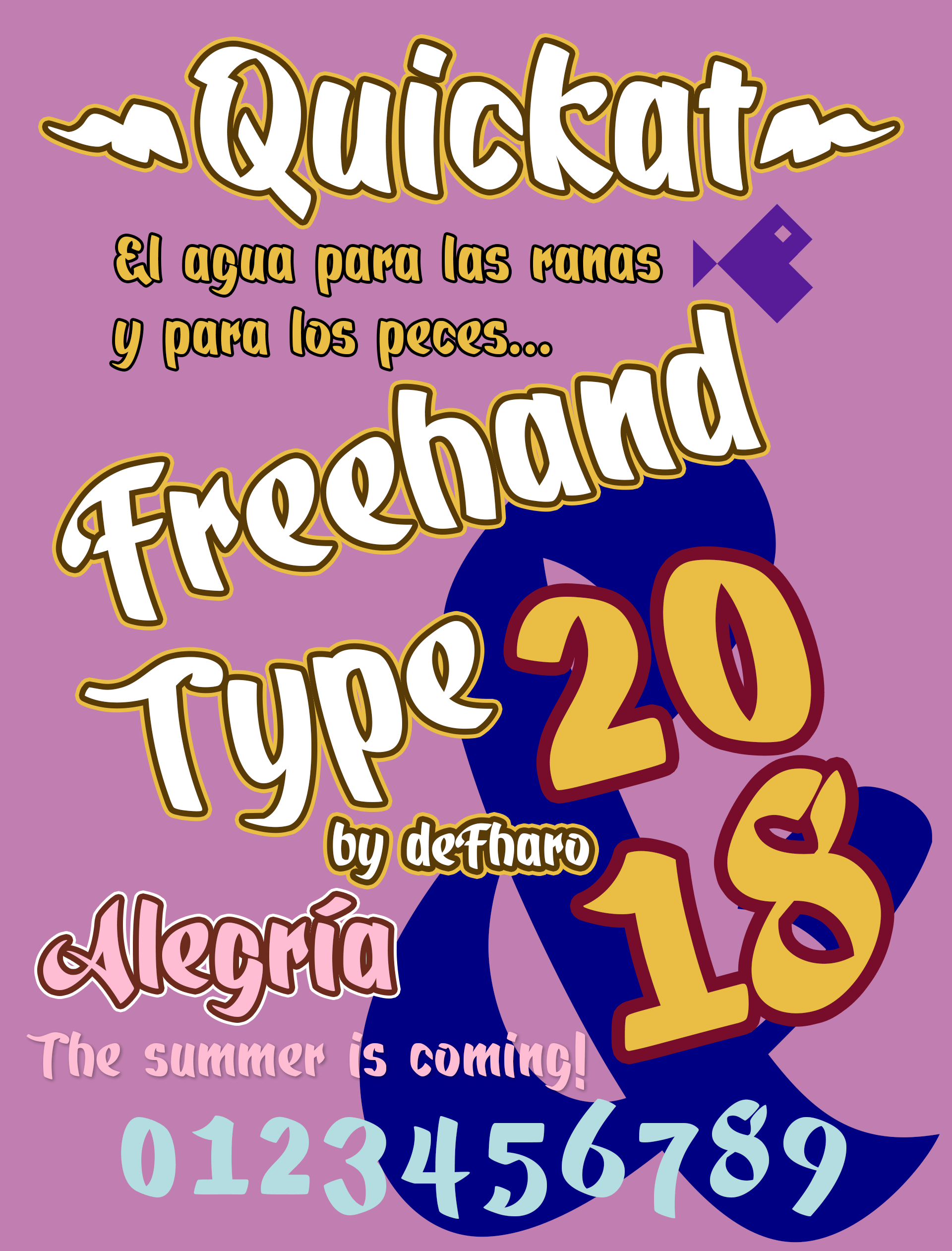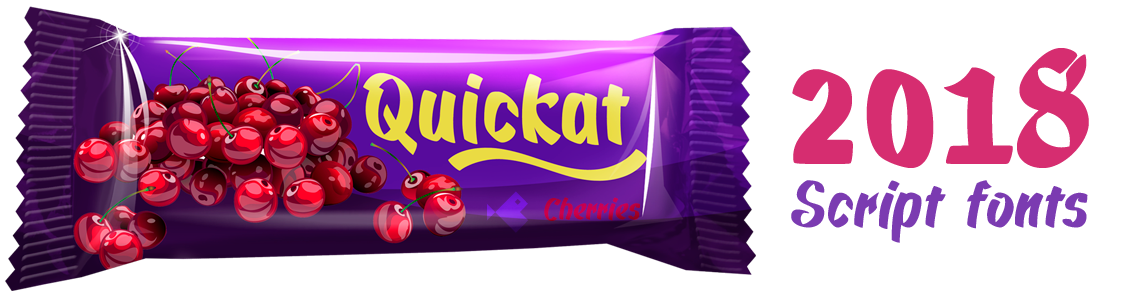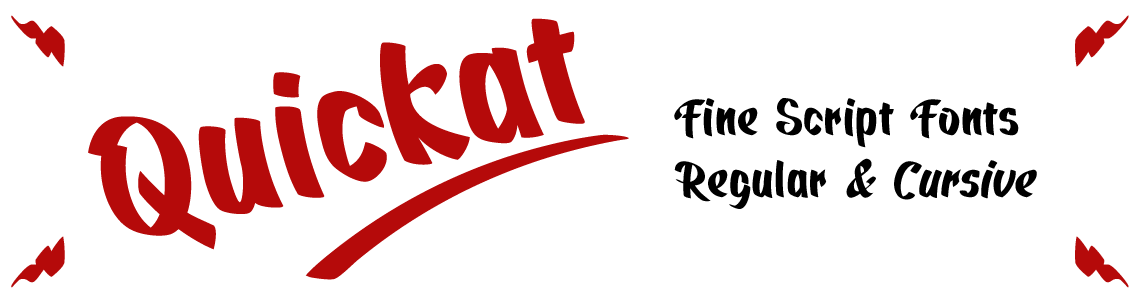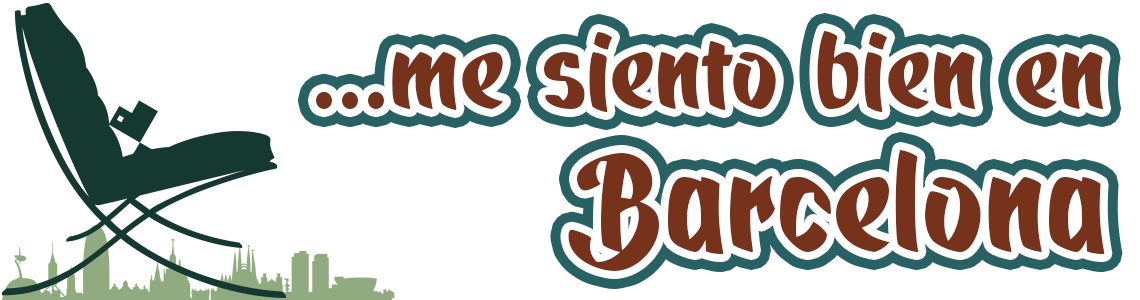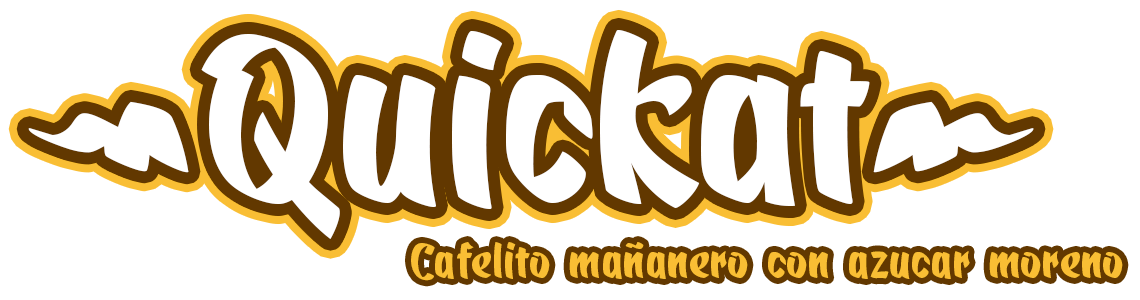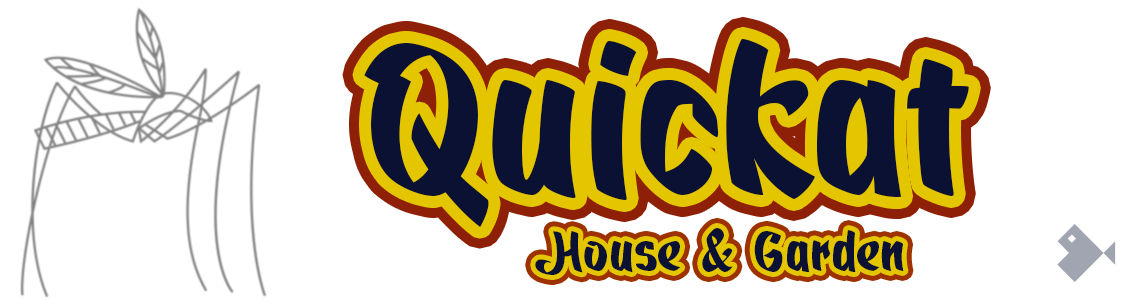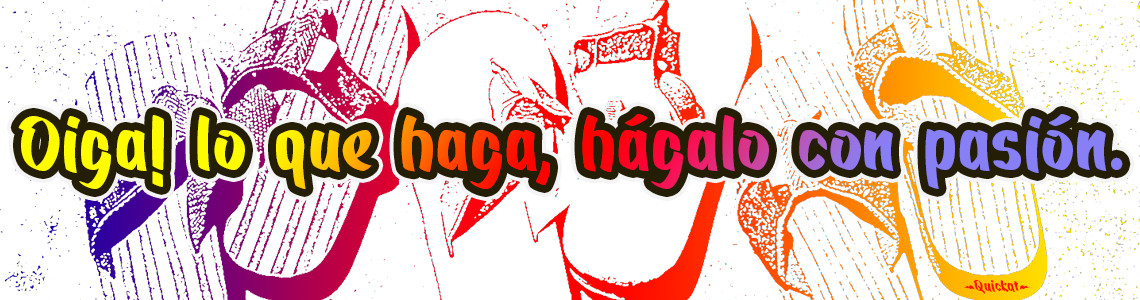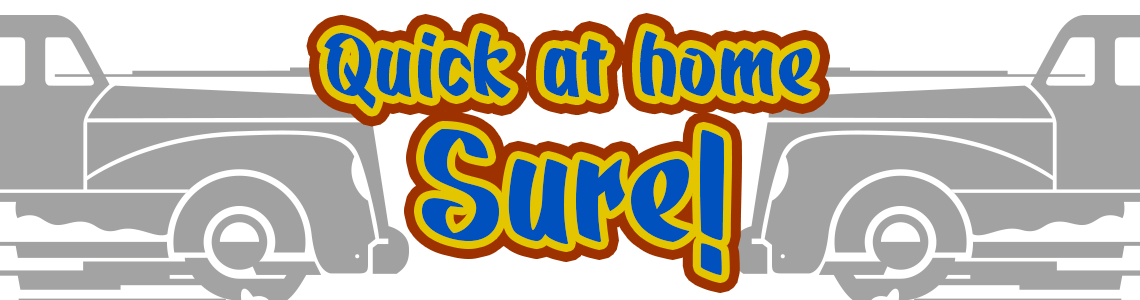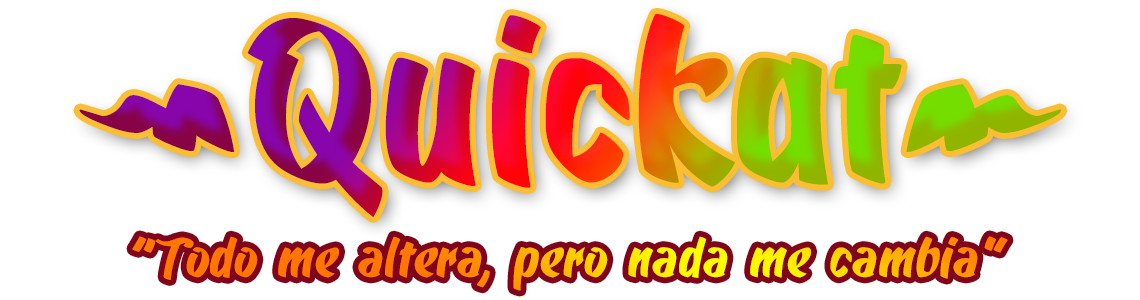
Quick at work!
Estilo: Handwritten, Calligraphic, Script, Ornamented
Proporción: Regular & Cursiva
Glyphs: 466
Funciones OpenType: All Alternates, Denominators, Discretionary Ligatures, Extended Fractions, Historical Forms, Inferiors, Kerning, Localized Forms, Numerators, Oldstyle Figures, Ordinals, Ornaments, Scientific Inferiors, Slashed Zero, Standard Ligatures, Subscript, Superior letters, Superiors, Superscript, Swash, Terminal Forms.
Esta fuente está dibujada a mano con pluma siguiendo unas proporciones basadas en los números de Perrin aplicada completamente a la letra H mayúscula y desde esta letra calculadas todas la proporciones del resto del abecedario según unas fórmulas matemáticas que llevo perfeccionando y poniendo en práctica en mis últimas fuentes.
Quickat es ideal para diseñar tarjetas de felicitación o bodas, posters, titulares llamativos o pequeños textos donde se busque un contraste entre este estilo manual frente a las fuentes neutrales como las Sans o las Serif. Acompaño a la versión regular otra cursiva con una inclinación de 12°.
La fuente «Quickat» dispone en su versión comercial de un juego de 466 glifos (Latin Extended-A), con soporte para cualquier idioma europeo o centro europeo. Quickat font también incluye funciones OpenType (Compatibles con InDesign, QuarkXpress, Photoshop e Illustrator.